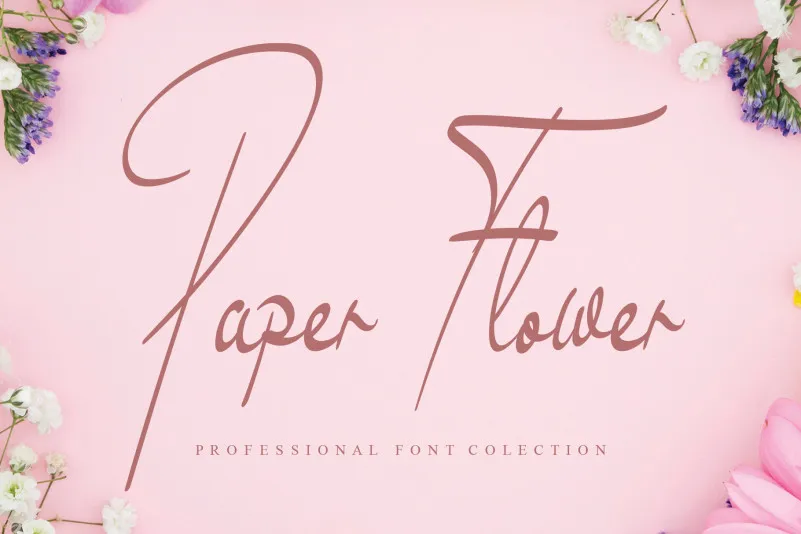
Paper Flower Handwritten Font – Download Grátis
A Paper Flower Handwritten Font é uma elegante tipografia script que transmite sofisticação e estilo contemporâneo. Desenvolvida meticulosamente para atender a necessidade de personalização, essa fonte não apenas adiciona um toque refinado aos seus projetos digitais, como também oferece um tom suave e envolvente à sua comunicação visual. Ideal tanto para design gráfico quanto para criação de conteúdo online, esta fonte traz um aspecto autêntico e natural que se integra perfeitamente em qualquer projeto. Seja ela usada para títulos chamativos ou para desenhar textos legíveis com facilidade, a Paper Flower Handwritten Font é uma escolha inteligente para quem busca criar algo especial e de qualidade. Com sua mistura única de elegância e modernidade, esta fonte proporciona um toque diferenciado que pode transformar qualquer projeto em uma verdadeira obra de arte. Ela é perfeita para designers gráficos e criadores de conteúdo que buscam algo mais do que apenas uma simples fonte; elas estão buscando uma conexão visual que transmita a essência da marca ou proposta de produto de maneira única e envolvente.